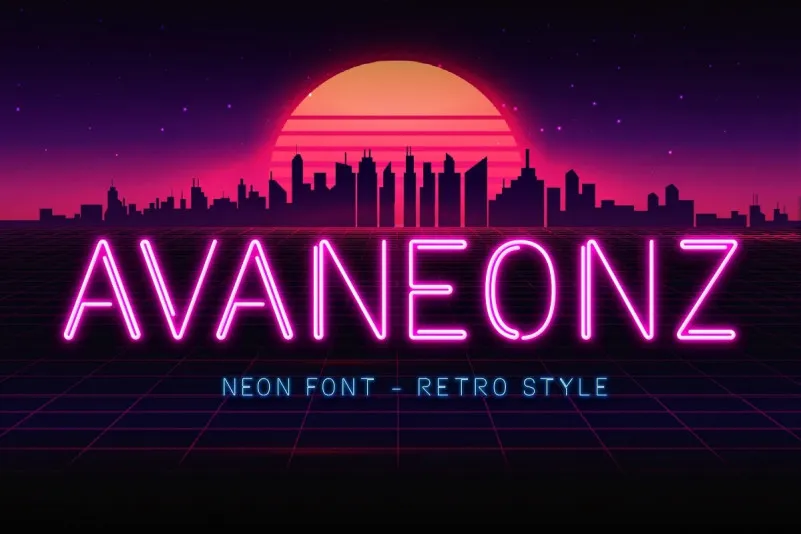
A Avaneonz Font é uma exuberante tipografia para display projetada para designers que desejam capturar a essência da iluminação neon tradicional de maneira digital. Inspirada no neon, esta fonte oferece aos criativos o poder de replicar com precisão e elegância letra originalmente feita à mão. Com formas de letras mínimas e ângulos arredondados perfeitamente suaves, a Avaneonz emite uma sensação realista dos raios de neon, exibindo linhas que terminam livremente sem ponteiros finos. Esta fonte é perfeita para aqueles que desejam incorporar efeitos de luz luminosa nas suas criações digitais ou até mesmo para projetos de design de assinaturas neon no mundo real. Um verdadeiro atalho à arte dos artistas visuais, a Avaneonz abraça o poder do design digital para transformar conceitos em realidade através da iluminação e da letra.